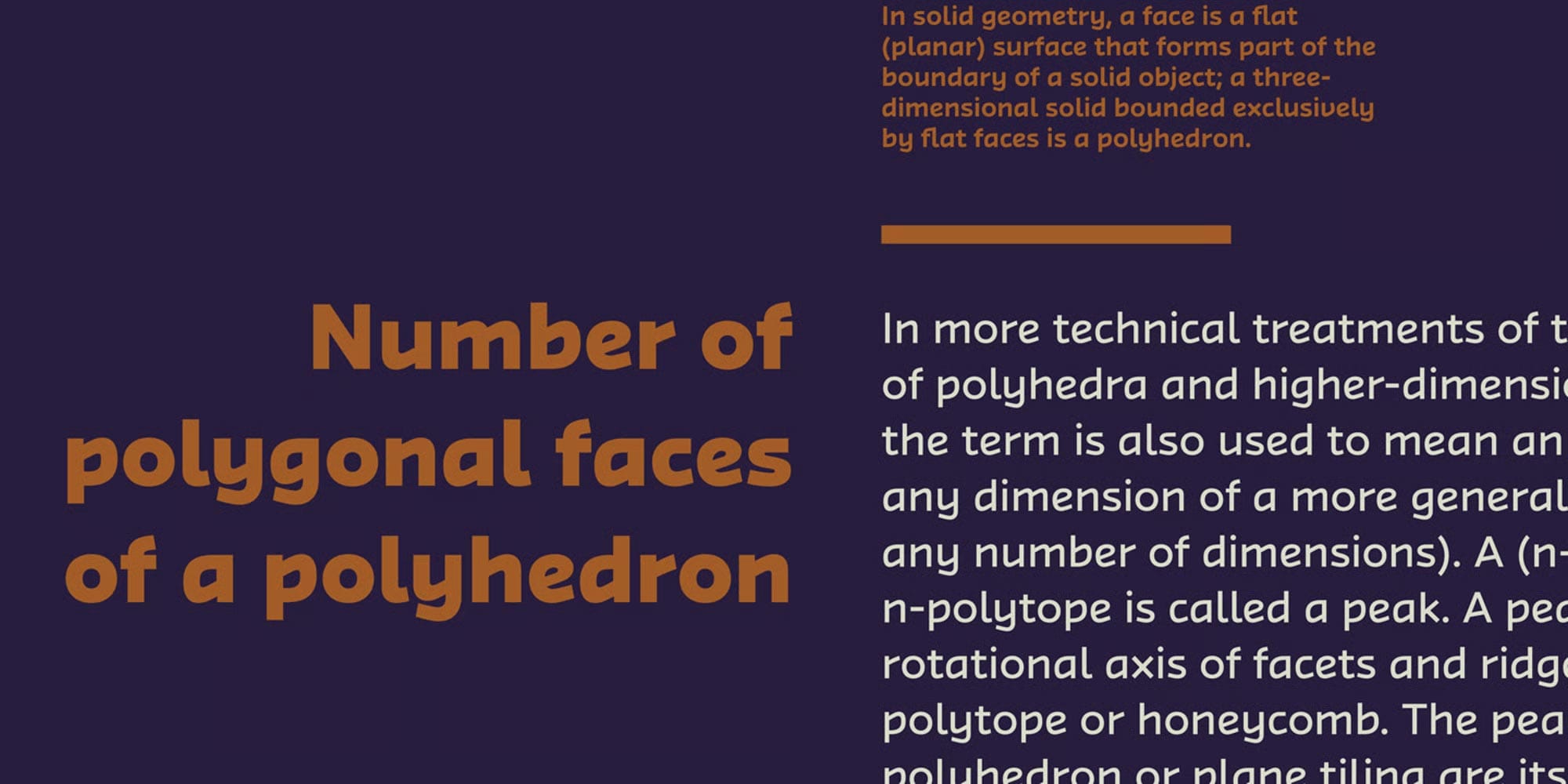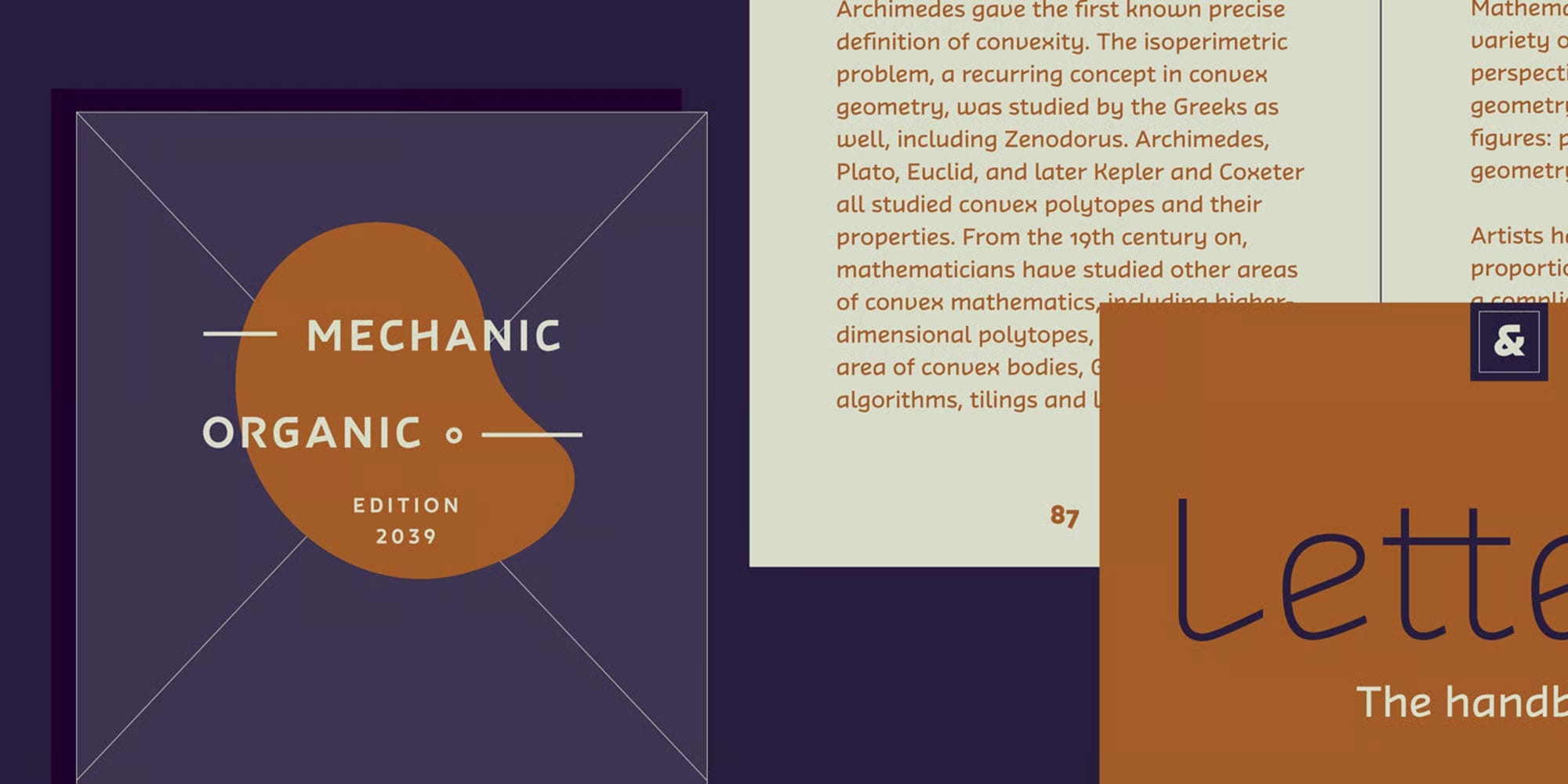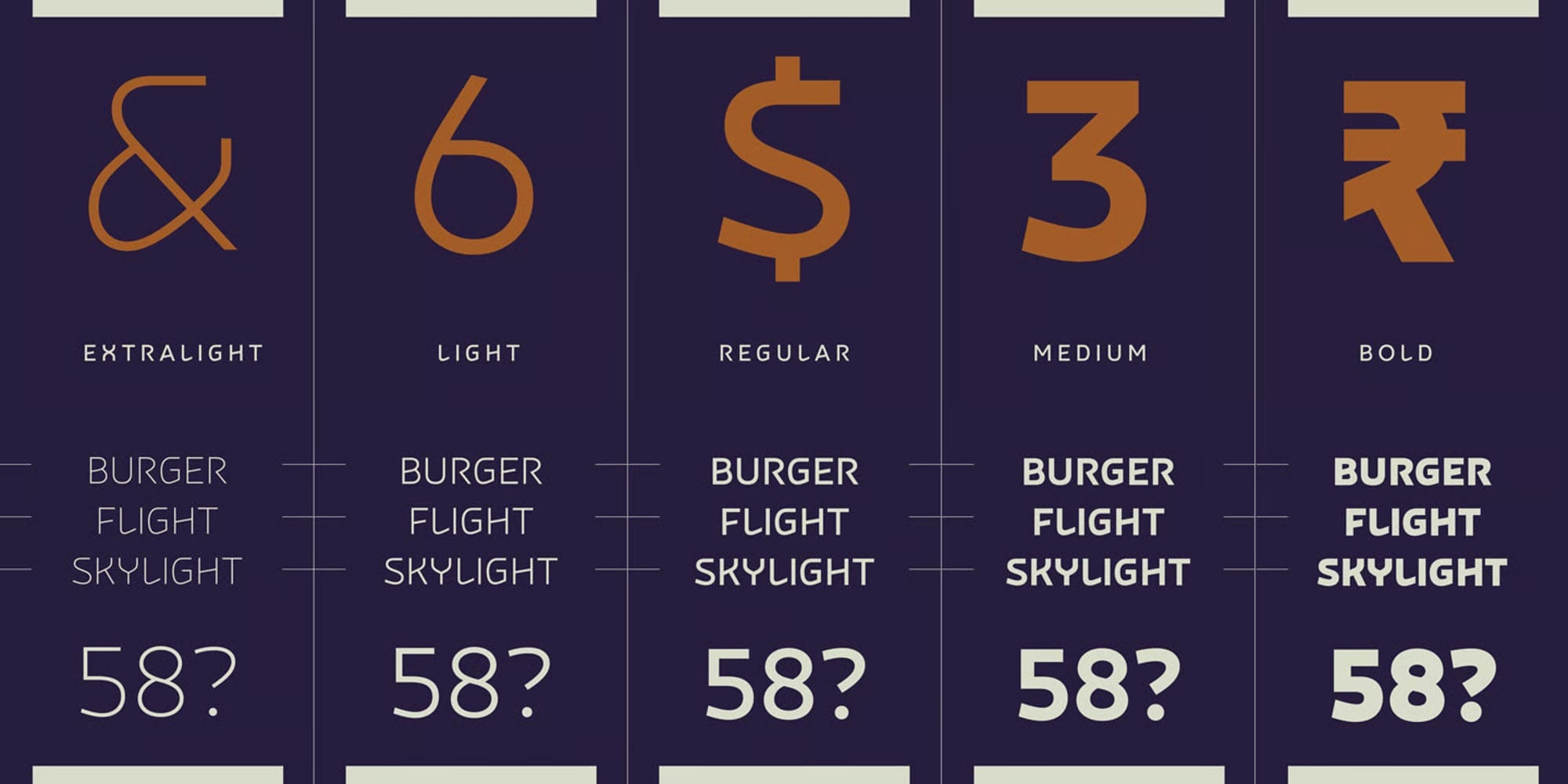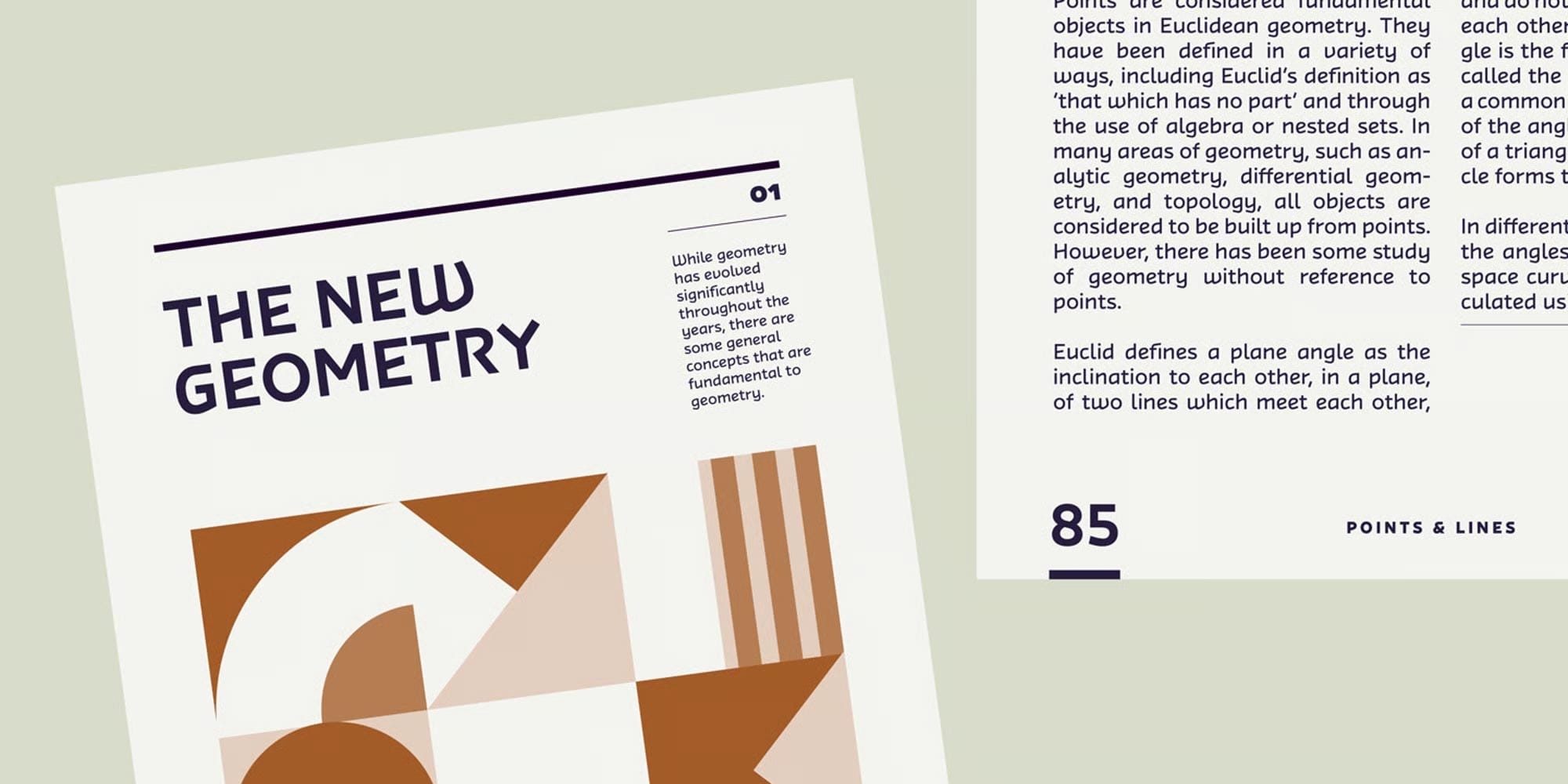
Hedra Font Family
Hedra Font Family là một họ font chữ sans-serif mang phong cách experimental sans được thiết kế bởi Sijya Gupta. Với các nét chữ có độ dày đồng nhất (monolinear strokes), Hedra kết hợp hai trường phái typography: geometric – nơi ‘O’ và ‘o’ gần như hình tròn hoàn hảo với điều chỉnh quang học nhỏ để tăng tính đọc – và humanist với các đường cong tự nhiên, mang hơi thở Art Nouveau từ đầu thế kỷ 20.
Điều làm Hedra nổi bật chính là sự cân bằng giữa vẻ ngoài kỹ thuật, futuristic (nhờ các đường chéo diagonal ở ‘A’, ‘B’, ‘E’) và yếu tố lịch sử tinh tế (bo tròn không truyền thống ở ‘K’, ‘V’, ‘W’). Đây là lựa chọn lý tưởng cho các designer muốn tạo ra nội dung vừa hiện đại vừa nghệ thuật, từ logo thương hiệu đến giao diện web responsive.
So với những font cùng nhóm geometric sans-serif như các typeface của TT Norms Pro, Hedra mang nét riêng nhờ các đường chéo (diagonal) mang hơi hướng lịch sử. Chính chi tiết này giúp Hedra giữ được vẻ hiện đại nhưng vẫn có chiều sâu, tạo nên sự khác biệt rõ rệt so với phong cách kỹ thuật thuần túy của TT Norms Pro.
Đặc điểm nổi bật của Hedra Font Family
Hedra không chỉ gây ấn tượng ở thiết kế mà còn được tối ưu với nhiều tính năng chuyên nghiệp, phục vụ tốt cho cả in ấn và kỹ thuật số:
• 5 trọng lượng (weights): ExtraLight, Light, Regular, Medium và Bold – linh hoạt cho mọi mục đích thiết kế, từ tiêu đề thanh mảnh đến đoạn chữ đậm nổi bật.
• Bộ ký tự phong phú: Hỗ trợ hơn 100 ngôn ngữ, bao gồm tiếng Anh, Pháp, Đức và nhiều ngôn ngữ châu Phi như Swahili và Zulu. Mỗi style chứa 453 glyphs đầy đủ: chữ hoa, chữ thường, số lining / oldstyle và dấu câu hoàn chỉnh.
• Tính năng OpenType nâng cao: Cho phép thay thế các đường chéo cong ở “K”, “X”, “Y” bằng phiên bản thẳng hơn, tạo cảm giác kỹ thuật và hiện đại.
• Tối ưu tính đọc (readability): Dù mang tinh thần experimental, Hedra vẫn được điều chỉnh optical một cách tinh tế để đảm bảo khả năng đọc rõ trên màn hình và bản in.